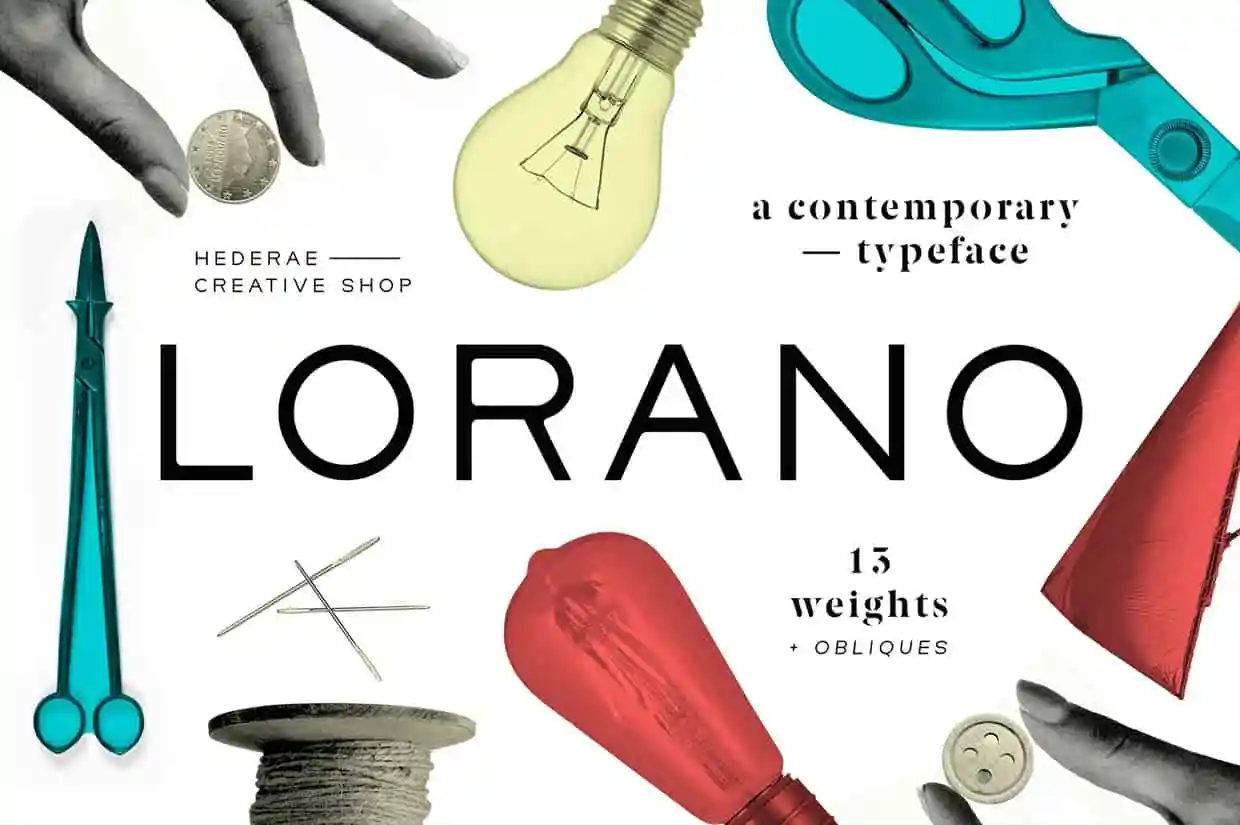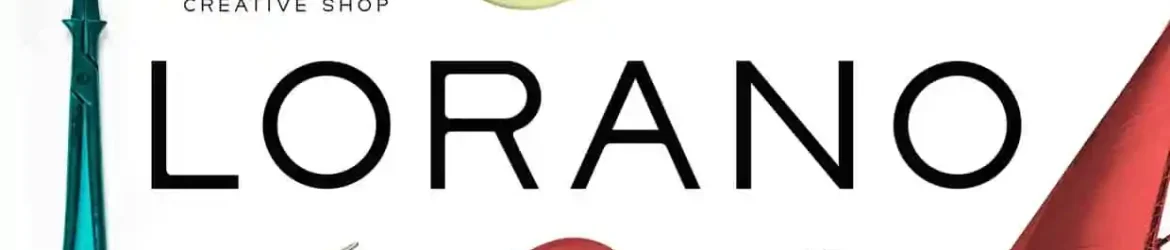
Lorano Typeface – Download Grátis
A Lorano Typeface é uma elegante tipografia sans-serif criada pelo Hederae Creative Shop, que oferece uma linguagem minimalista e moderna para qualquer projeto visual. Esta fonte foi projetada com um equilíbrio cuidadoso entre legibilidade e estética contemporânea, fazendo-a perfeita para aplicações digitais como websites ou aplicativos de uso quotidiano. Seu design fluido e seu caráter clean destacam-se por sua facilidade de leitura, tornando-a uma opção confiável para qualquer necessidade que exige legibilidade em grande escala, desde logotipos e sites até materiais publicitários e editoriais. Com o designer Hamilton ao comando, a Lorano oferece um conjunto completo de características e configurações personalizáveis para atender às mais variadas demandas. Suas linhas leves e retas evocam uma presença moderna e clean, capaz de transmitir mensagem clara e eficaz em qualquer contexto. Essa tipografia é particularmente versátil e adaptável a diversos estilos de design, tornando-a uma escolha ideal para designers e criativos que procuram um recurso gráfico atemporal.